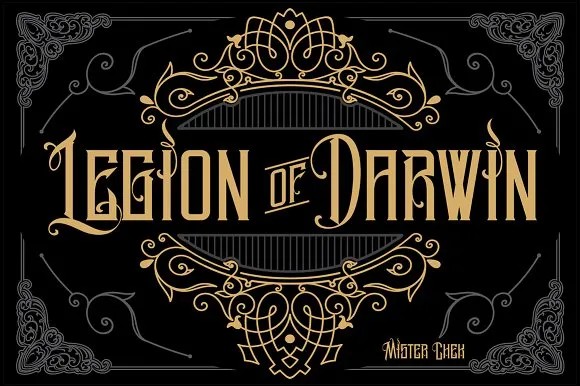
A fonte Legion of Darwin é uma escolha perfeita para designers que buscam uma solução moderna e versátil para seus projetos digitais. Este Gothic Font foi criado pelo talentoso designer Mister Chek, oferecendo a você um conjunto de letras distintas e poderosas. Ideal tanto para design pessoal quanto comercial, o Legion of Darwin traz consigo uma paleta vibrante de opções que vai desde linhas finas até bold expressivas. Seja para criar logos memoráveis ou adicionar um toque distinto em sites e materiais de marketing, essa fonte é uma ótima escolha. A descrição fornecida pelo autor sugere um uso pessoal apenas. Para obter o acesso completo à esta poderosa ferramenta de design e adquirir a licença comercial, basta visitar o link fornecido. Mister Chek também está disponível para responder suas perguntas ou se interessar em trabalhos especiais através do Instagram ou email. Sem dúvida, o Legion of Darwin é uma fonte que merece um lugar na sua coleção de recursos gráficos. Com estilo moderno e forte, ele pode dar um toque único a qualquer projeto digitado.